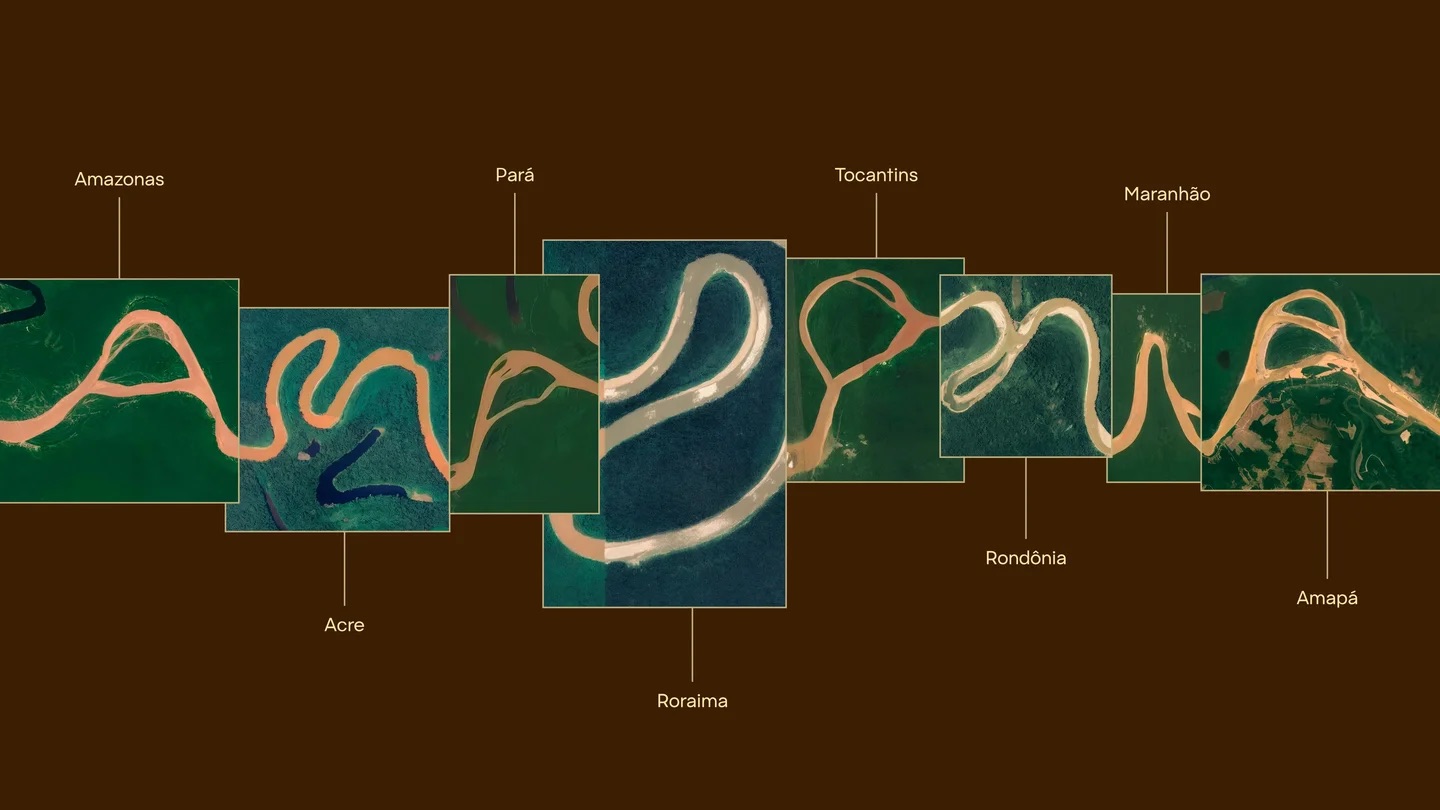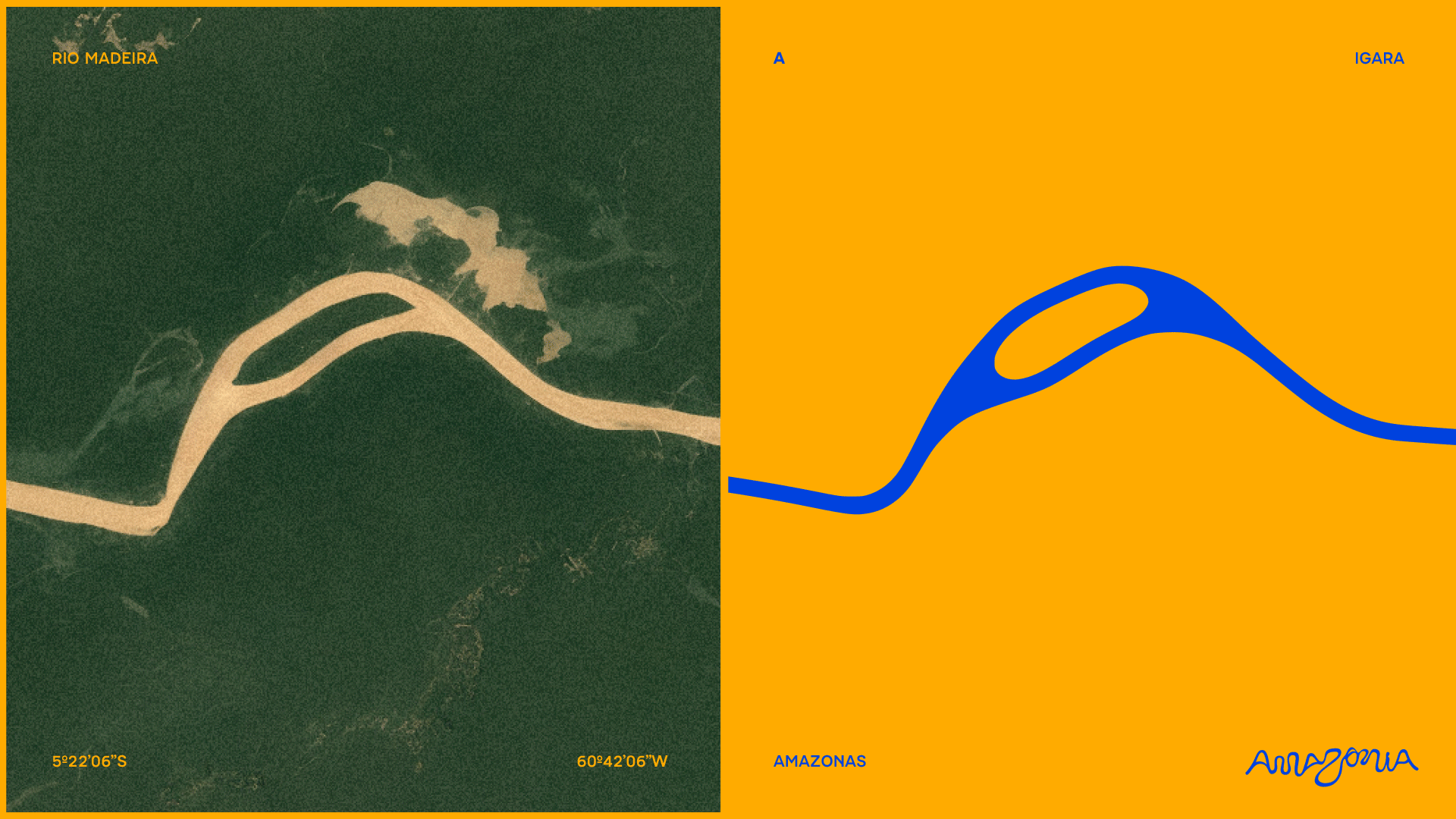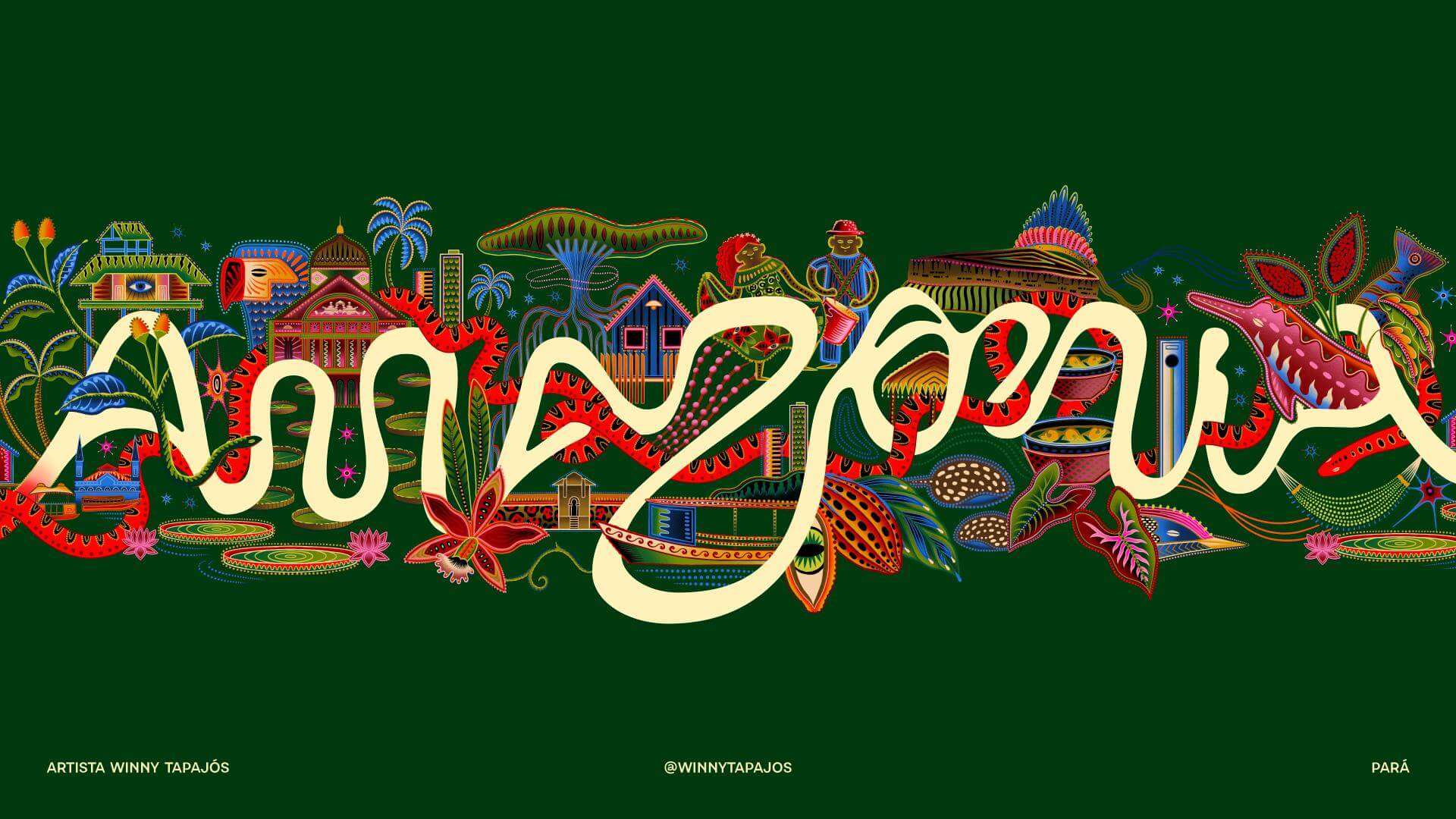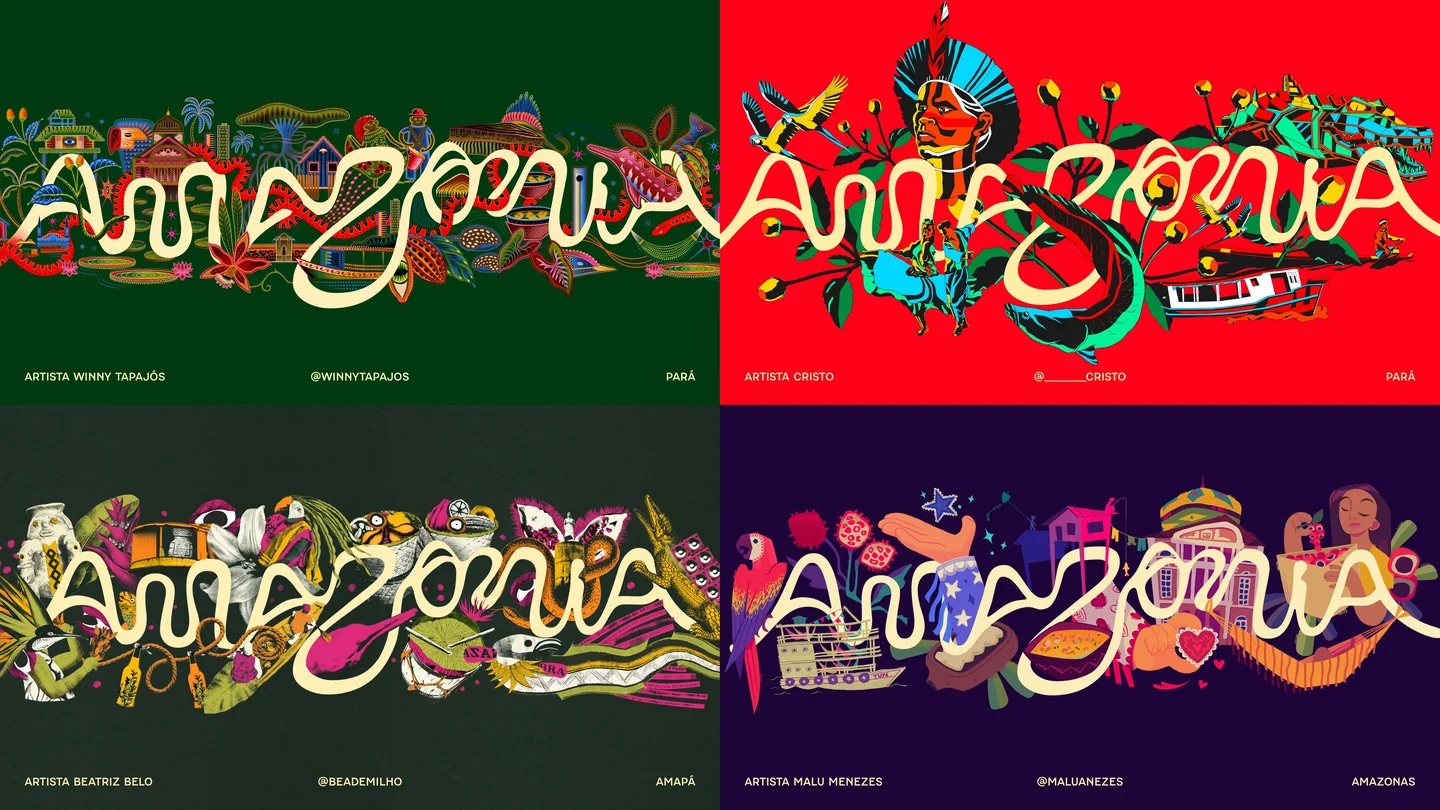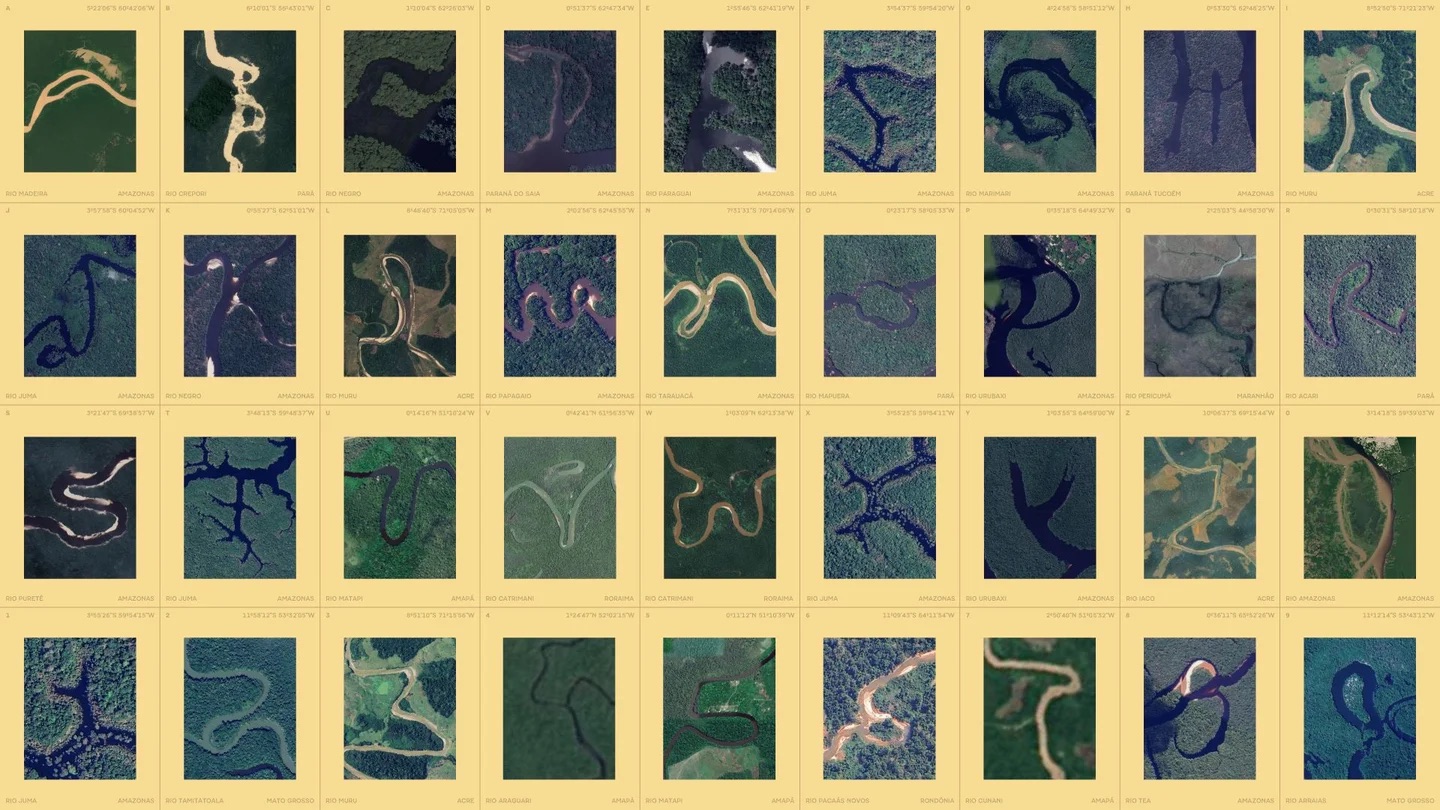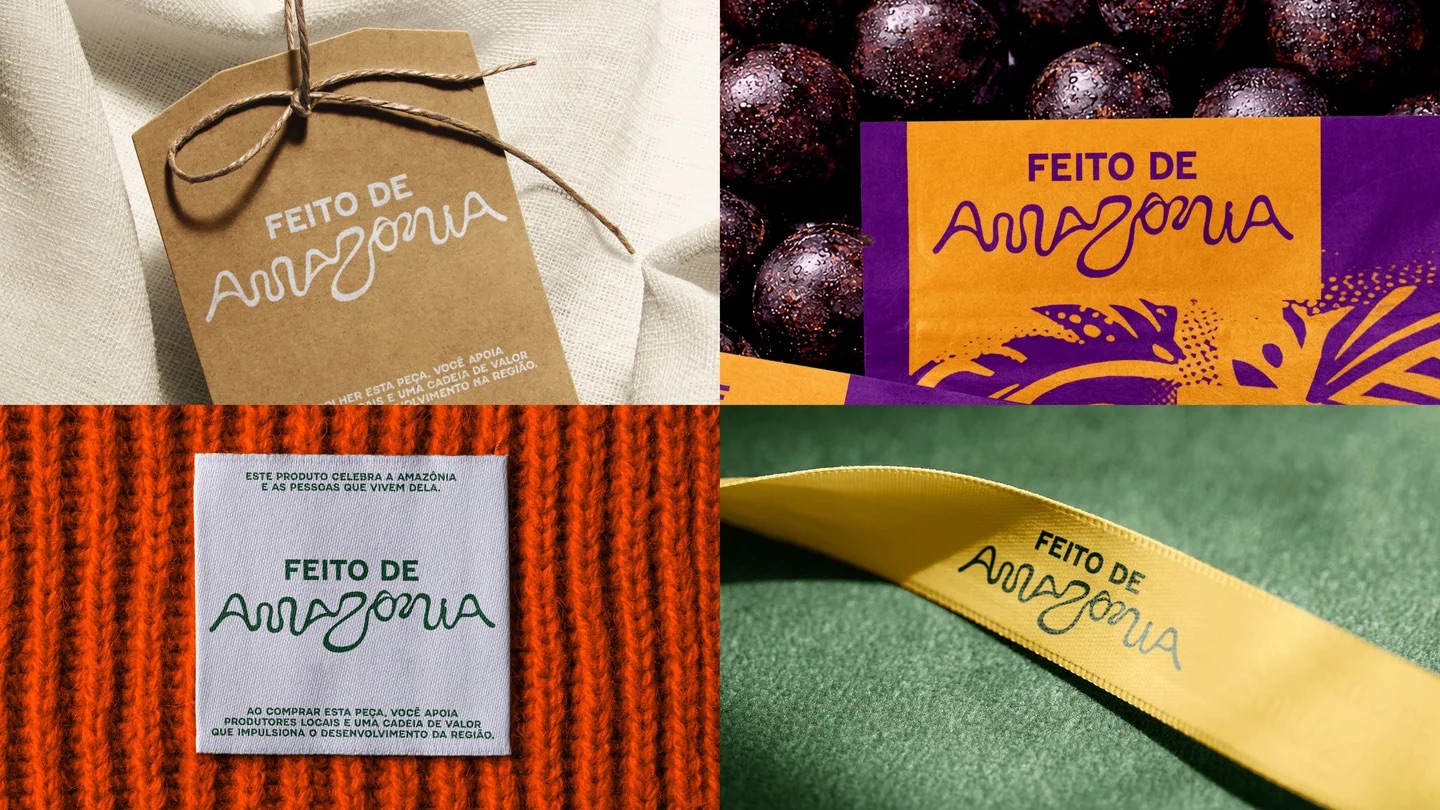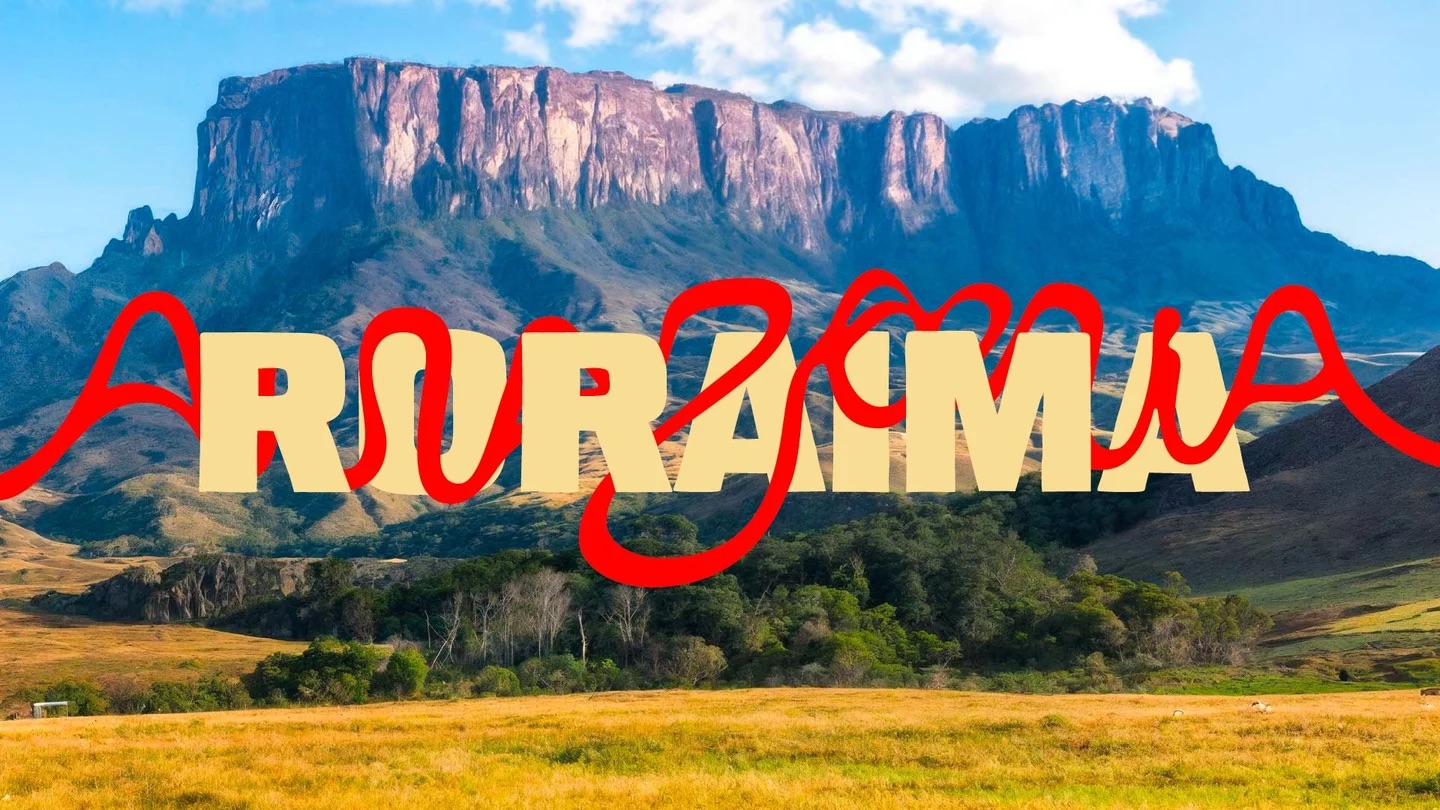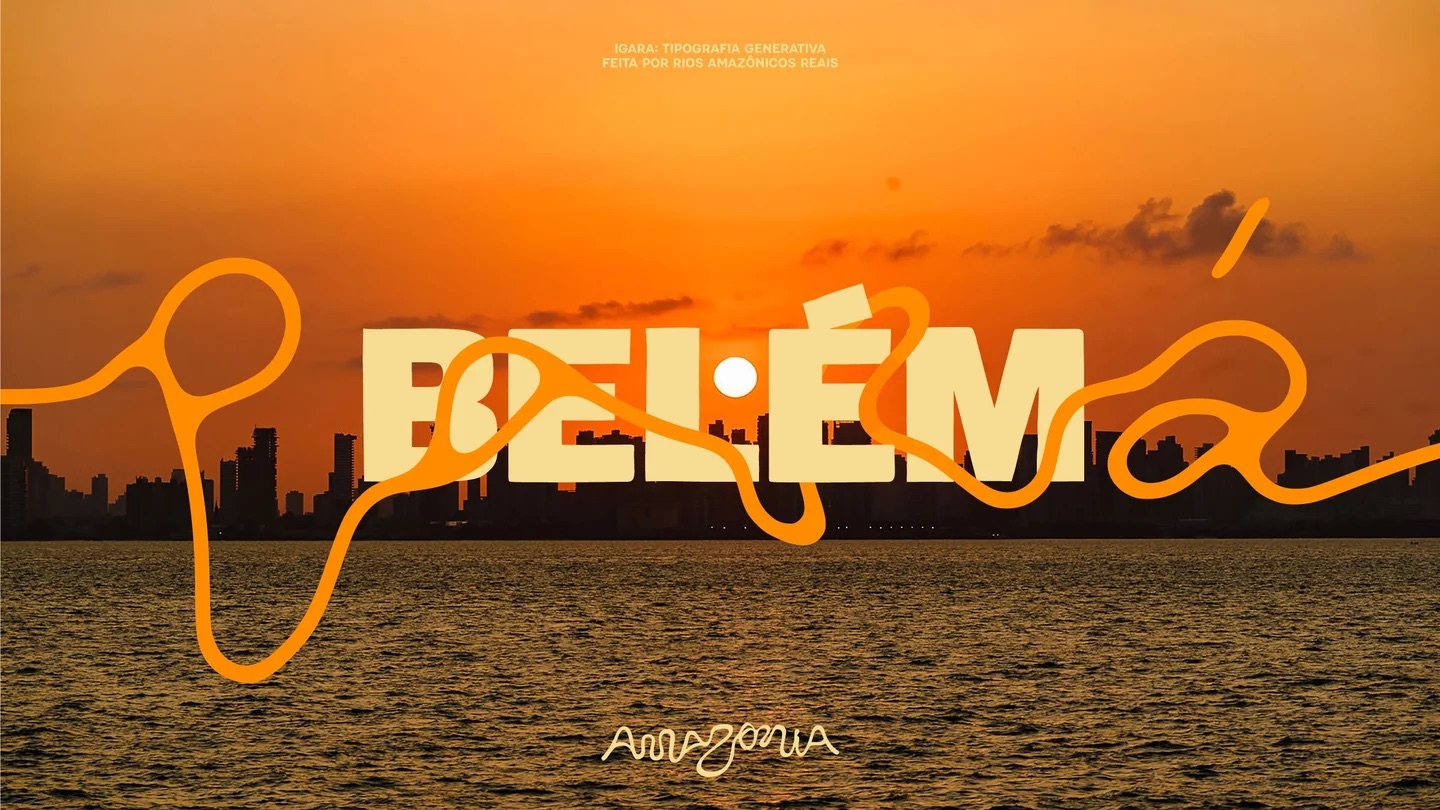
- L’Amazonie brésilienne se dote d’une identité visuelle unifiée, créée à partir des courbes réelles du fleuve et de ses affluents.
- Un alphabet complet a été conçu depuis ces formes naturelles, transformant la géographie du territoire en langage graphique unique.
- Pensée comme un système évolutif, cette identité vise à promouvoir la région, soutenir son économie et valoriser ses savoir-faire.
C’est un territoire immense, riche et multiple… mais qui n’avait jusqu’ici jamais parlé d’une seule voix. L’Amazonie brésilienne se dote aujourd’hui de sa première identité visuelle unifiée, pensée pour mieux rayonner à l’échelle nationale et internationale.
Imaginée par FutureBrand pour Embratur et RAI, cette nouvelle marque ne se contente pas de représenter la région. Elle en est littéralement issue, en puisant directement dans sa géographie pour créer un système graphique unique.
Une typographie dessinée par la nature
Plutôt que de concevoir un logo de manière classique, les équipes créatives ont choisi de partir du territoire lui-même. À partir de coordonnées réelles et d’images satellites, elles ont analysé les courbes du fleuve Amazone et de ses affluents.
De ce travail est né un alphabet complet, dont chaque lettre a été extraite des formes naturelles des rivières. Une approche radicale qui inverse le processus habituel du design, en transformant un paysage en langage visuel.
Une identité pensée comme un système vivant
Cette marque ne se limite pas à un logo figé. Elle a été conçue comme une identité évolutive, capable de s’adapter aux différents contextes et aux spécificités des neuf États qui composent l’Amazonie brésilienne.
Couleurs, motifs et éléments graphiques peuvent ainsi varier tout en conservant une cohérence globale. Une manière de refléter la diversité culturelle, naturelle et humaine du territoire, sans l’uniformiser.
Un outil au service du territoire et de son économie
Au-delà de l’image, cette identité vise à soutenir concrètement le développement de la région. Elle s’accompagne notamment d’un label “Feito de Amazônia”, destiné à valoriser les produits, savoir-faire et initiatives locales.
Pensée comme un levier pour le tourisme mais aussi pour la bioéconomie, cette marque ambitionne de renforcer la visibilité de l’Amazonie tout en soutenant les communautés qui la font vivre. Vous pouvez en apprendre davantage en vous rendant sur le site officiel.